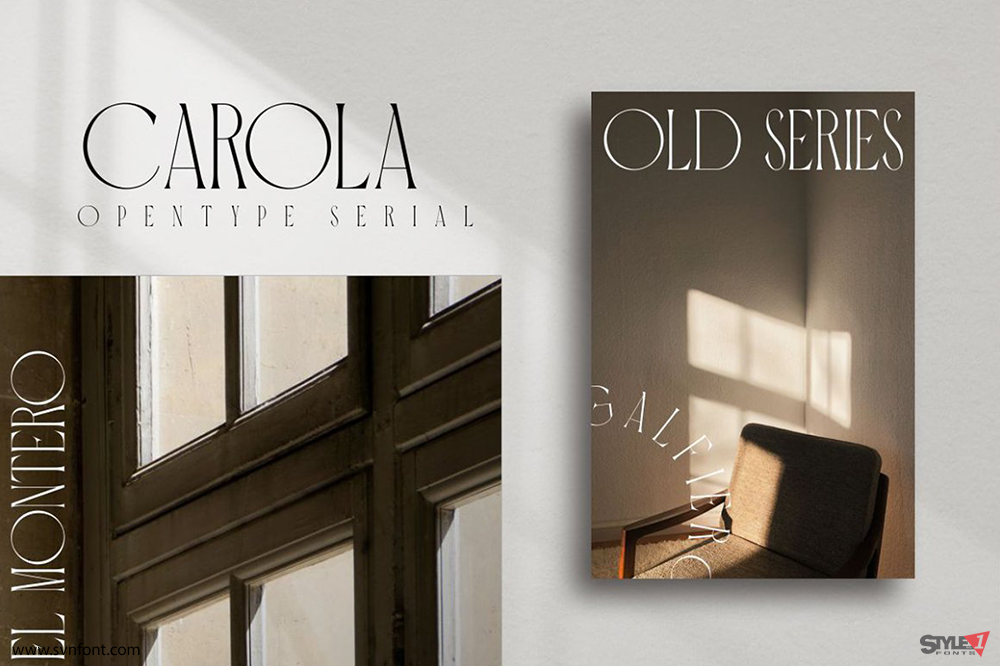
SVN Carola - Font chữ nét cao Việt hoá
Phông chữ Carola bao gồm các chữ cái viết hoa, chữ số, một loạt các dấu câu. Phông chữ Serif với phong cách hiện đại. Được tạo cho áp phích, thiết kế web, xây dựng thương hiệu, hình minh họa, huy hiệu và một số tác phẩm khác.
Nhà thiết kế: Muntab_Art